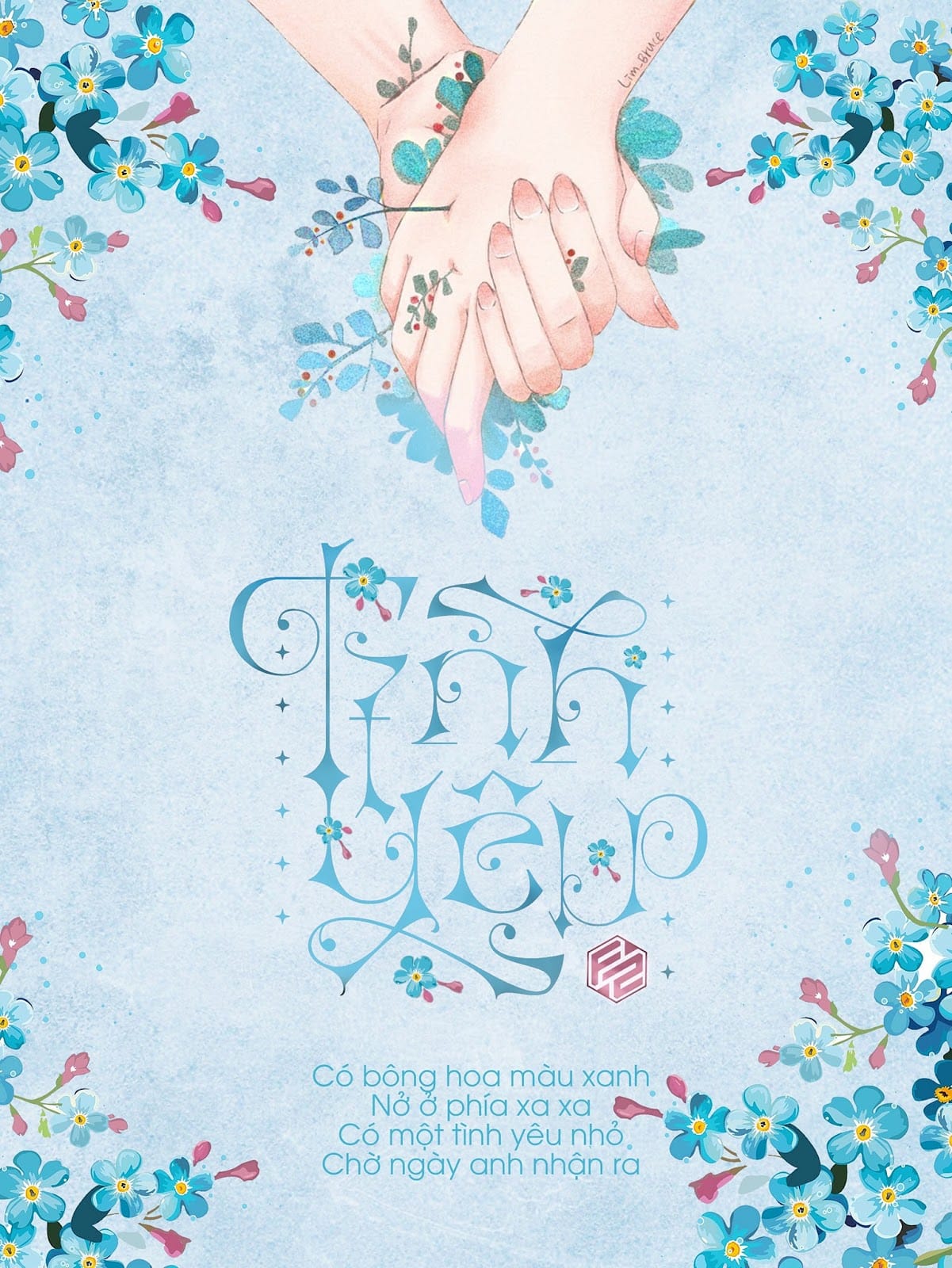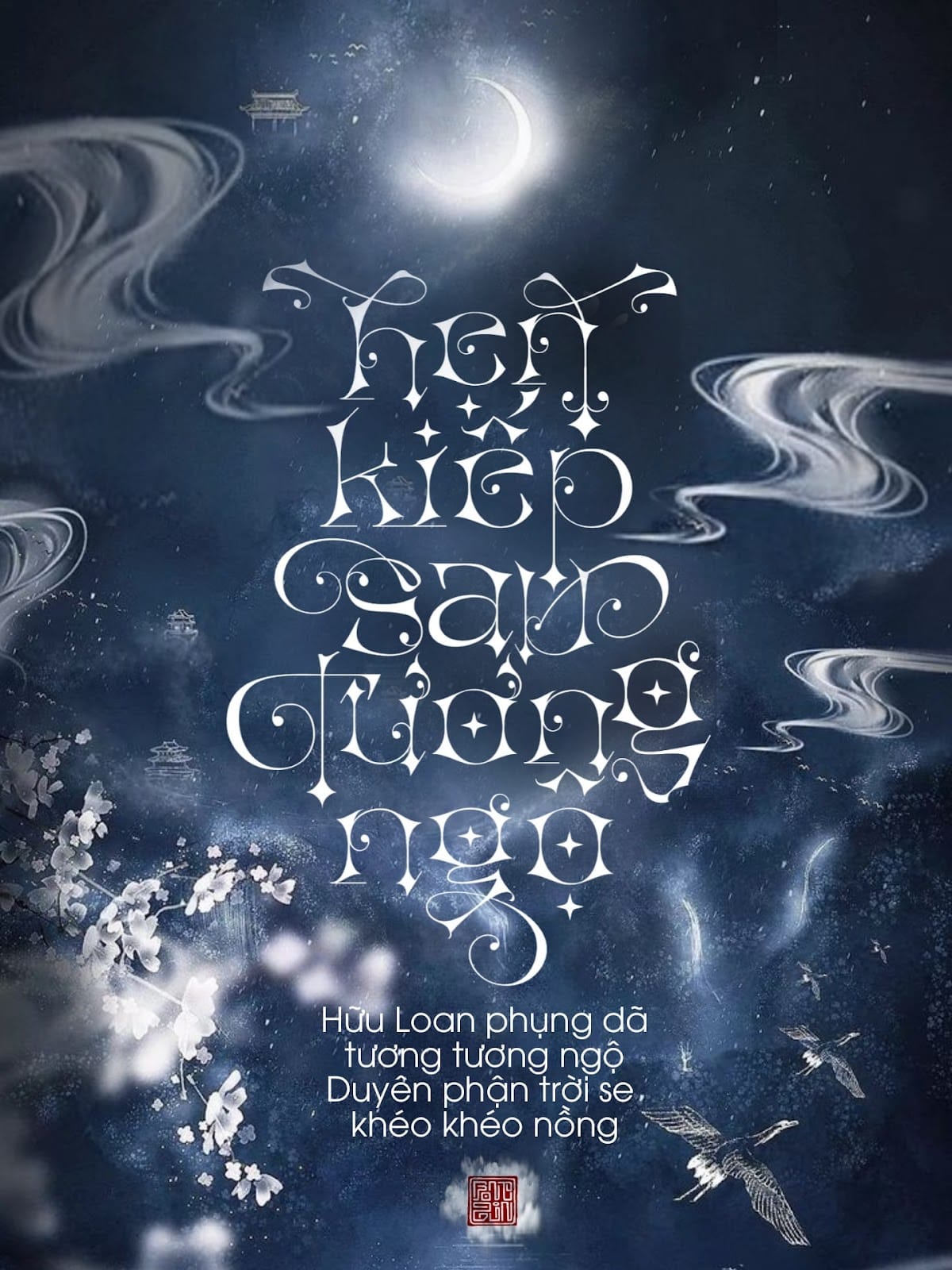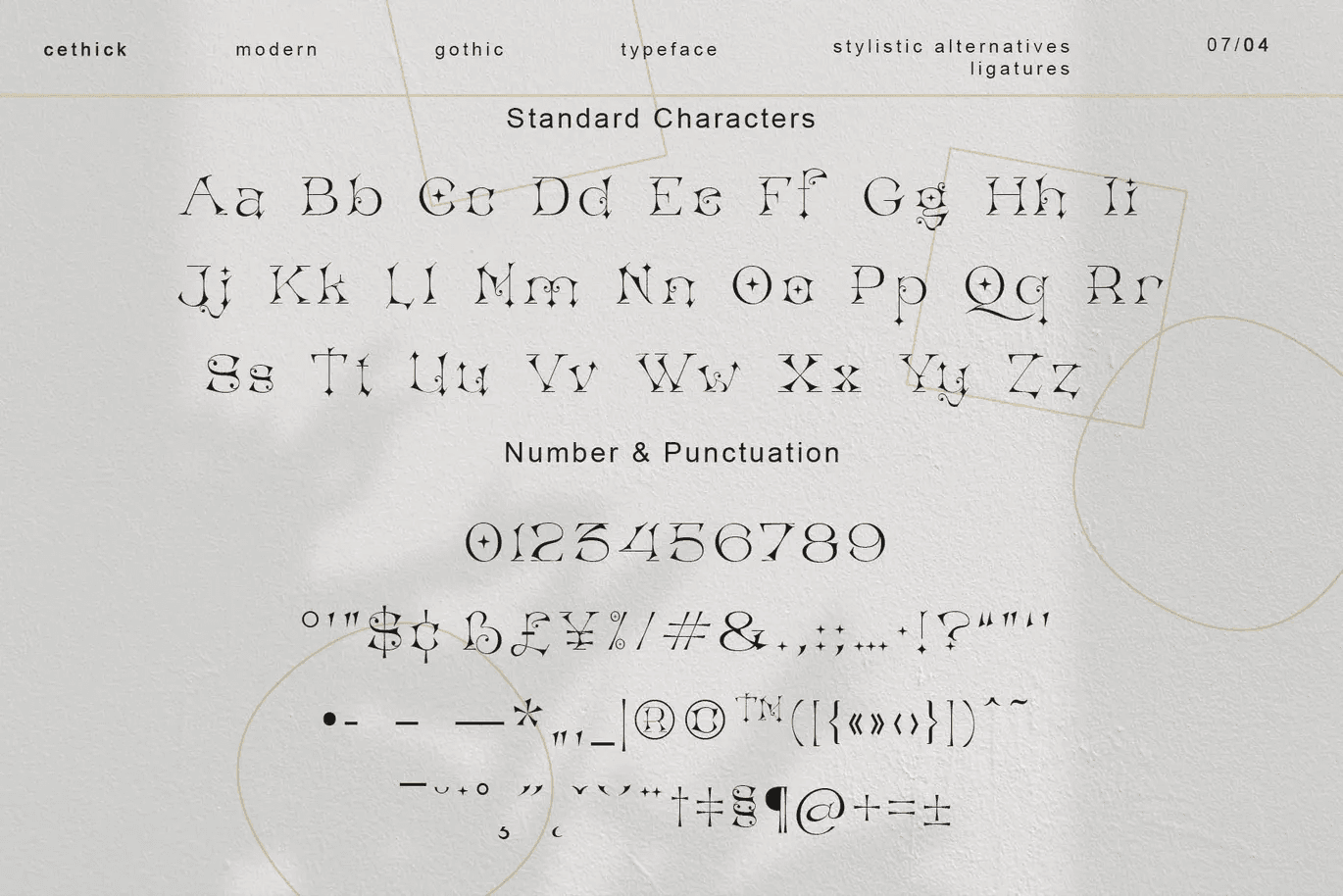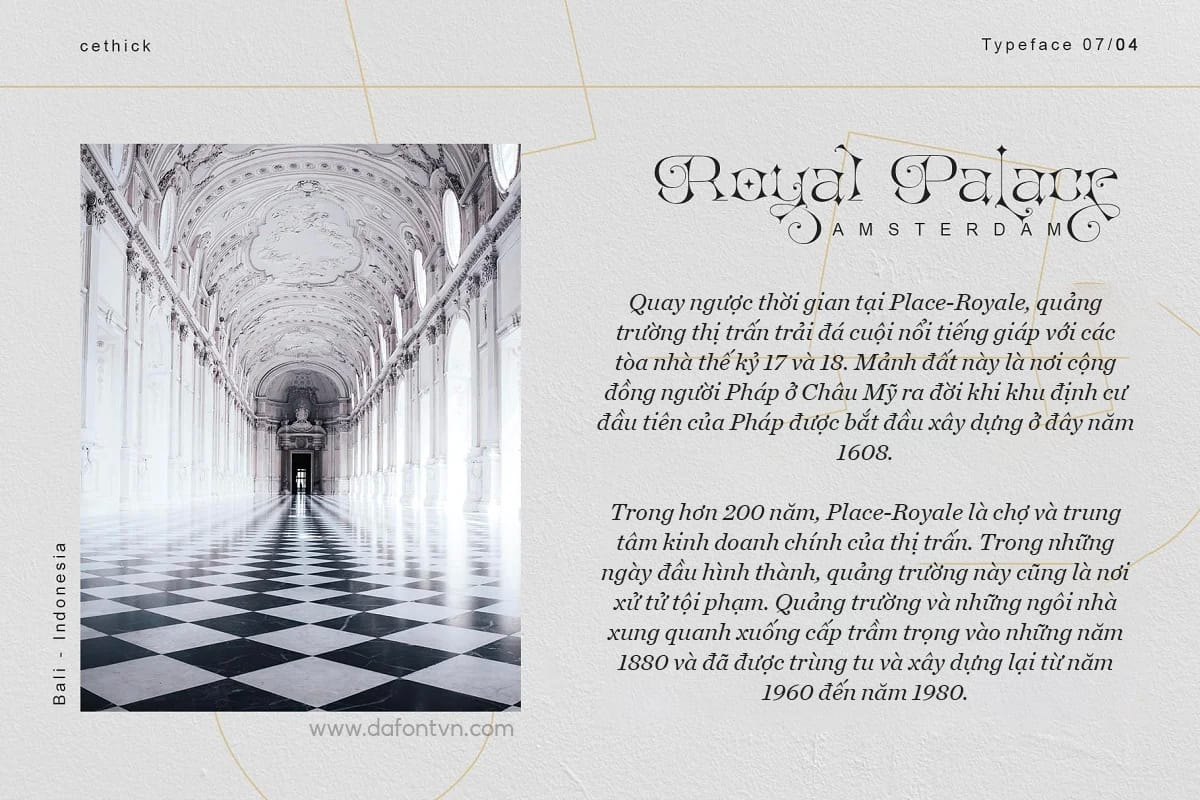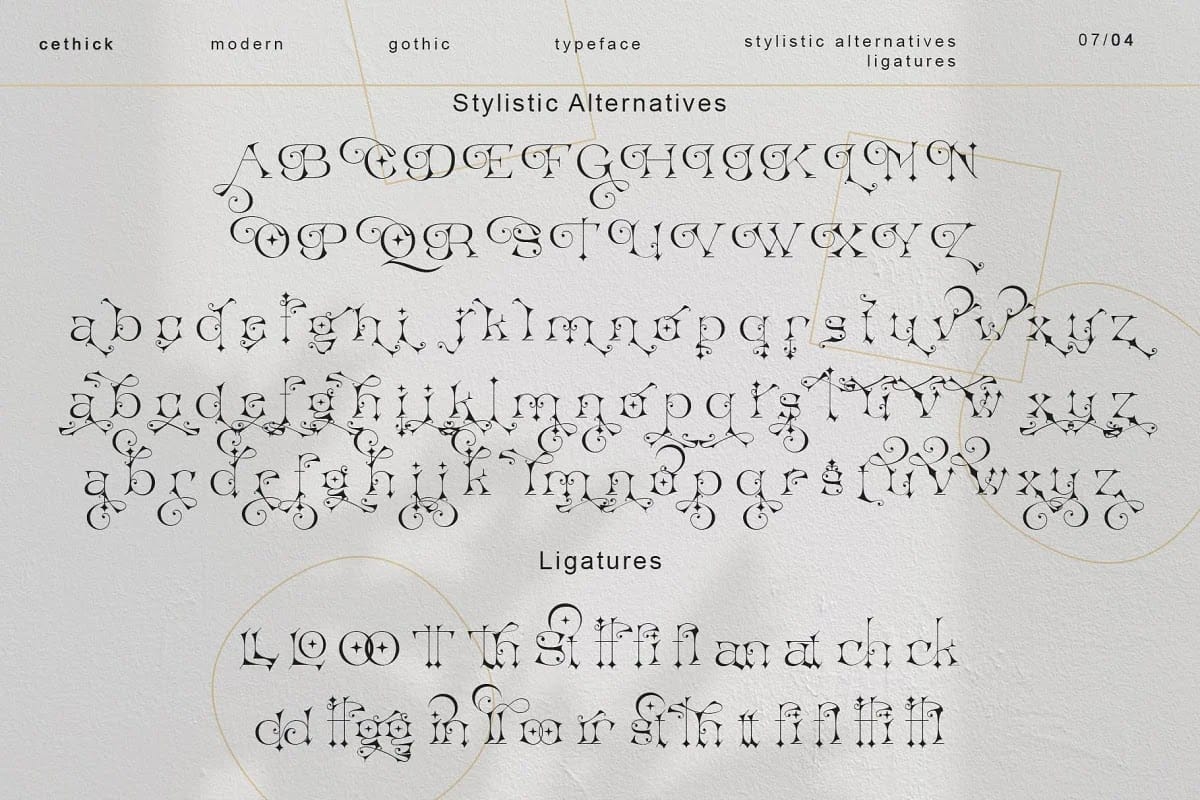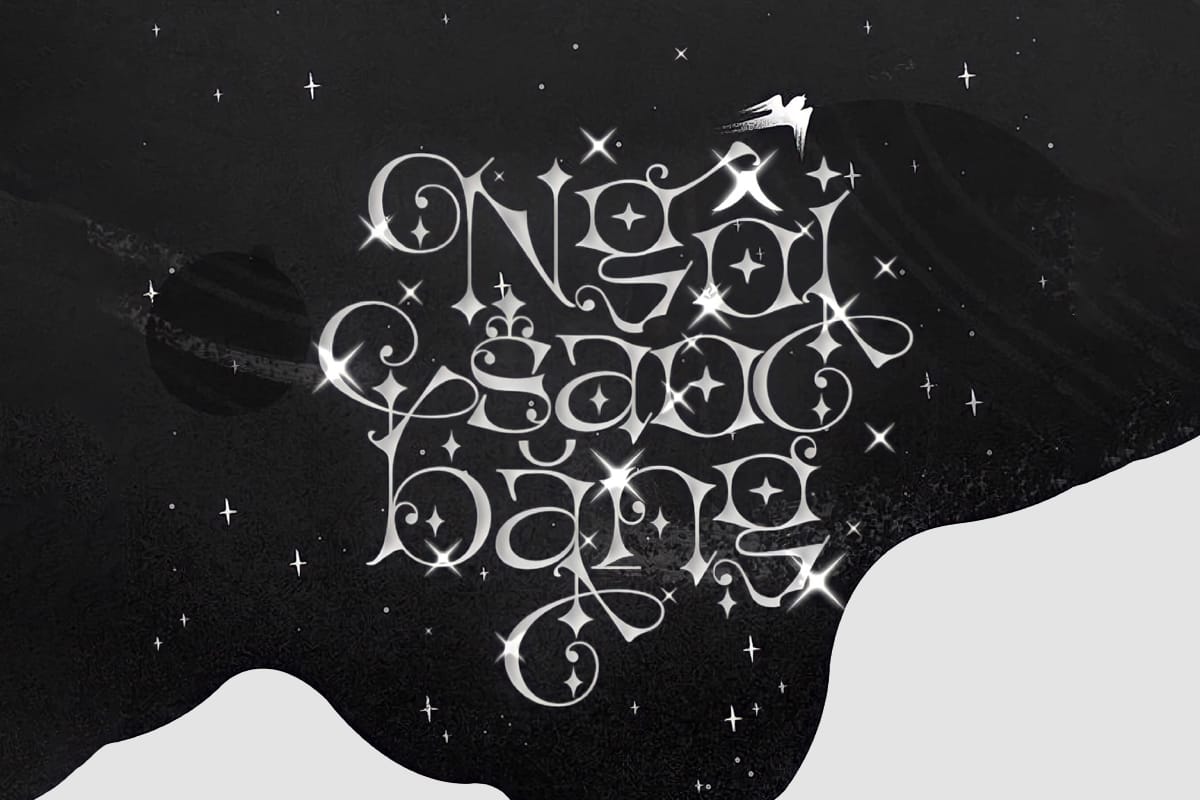
Font việt hóa Cethik là một phông chữ display cực kỳ thú vị và chân thực lấy cảm hứng từ font chữ gothic đầu những năm 1900. Phông được thiết kế hoàn toàn thủ công với các nét chữ có độ chi tiết cao và rất độc đáo. Cethik được mã hóa PUA vì vậy bạn có thể truy cập tất cả các glyph và swash rất dễ dàng. Font Cethik Việt Hóa đầy đủ bởi FZ, phù hợp cho các thiết kế tiêu đề, bìa truyện, typo, tạp chí…